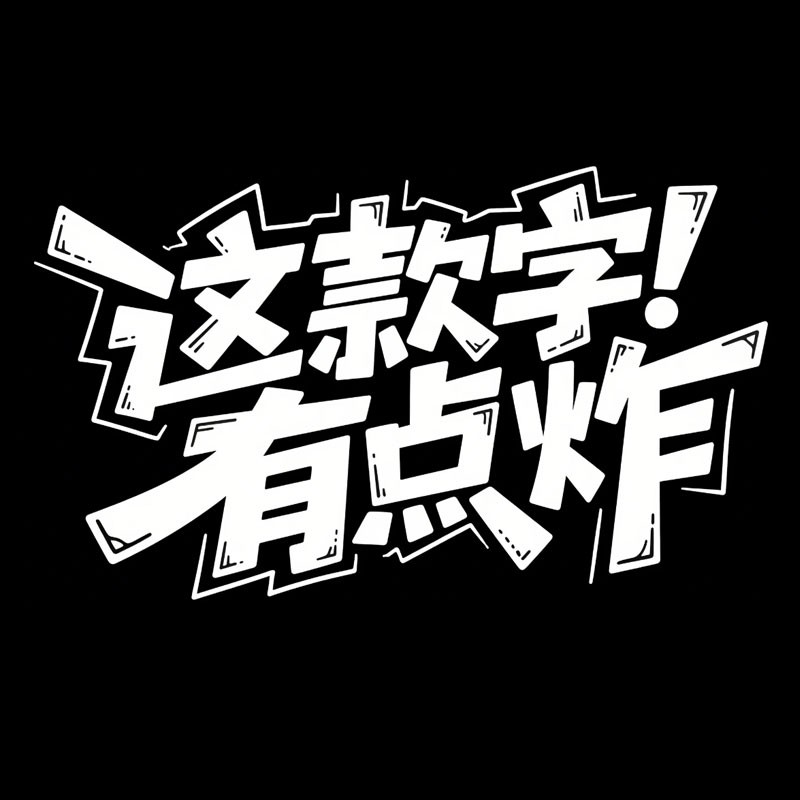
漫画式综艺字体,白字,纯黑色背景。 适用场合:充满趣味的娱乐节目宣传物料。字形结构:结构宽松,夸张、富有张力的不规则结构,部分笔画有明显的伸展和变形,避免过于规整和对称,展现自由、活泼的视觉感受。 笔画特征:采用一头粗一头窄的设计手法,笔画具有马克笔手绘质感,笔画中有漫画式的长短不一的镂空线条。 结构布局:重心较为灵活,部分笔画相互穿插、避让,整体具有强烈的视觉冲击力和独特的艺术风格